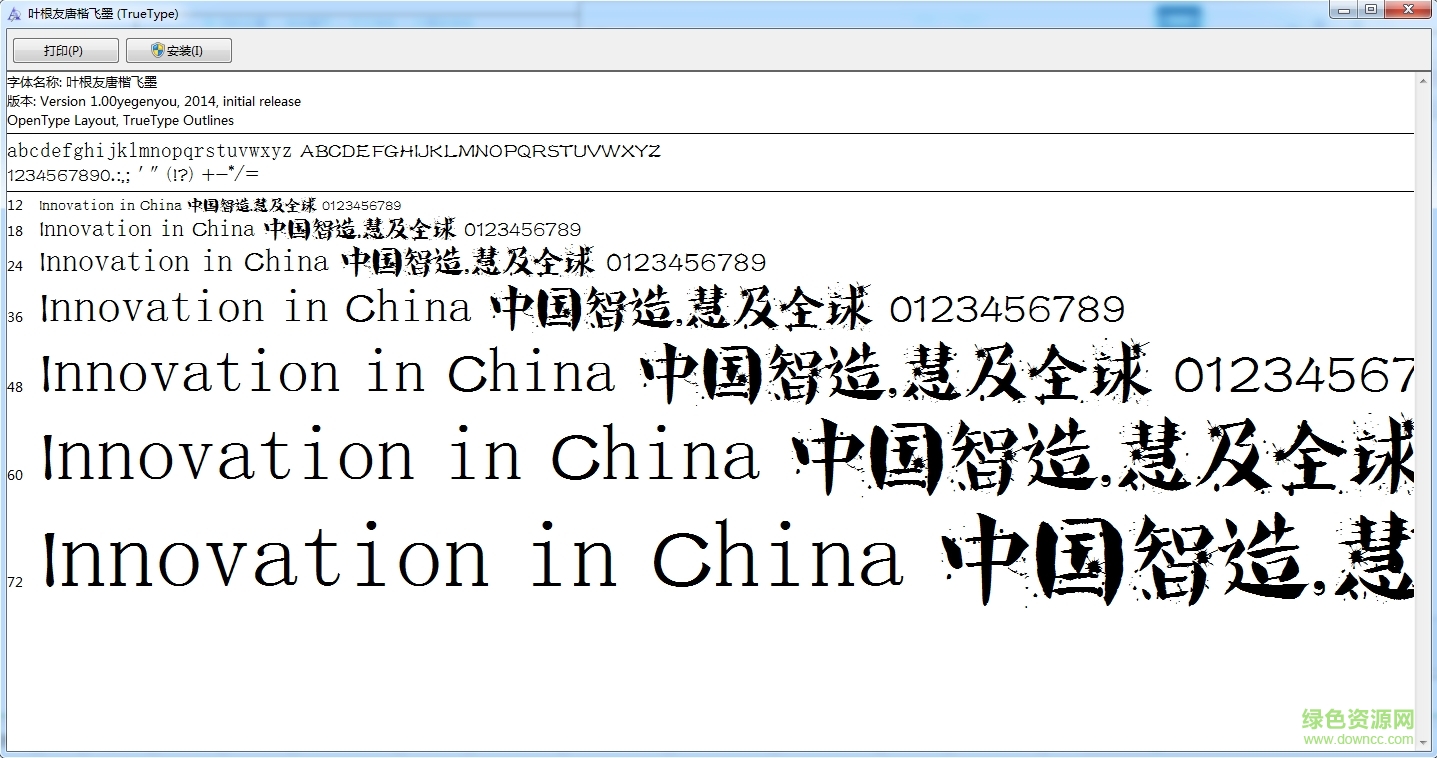
葉根友唐楷飛墨是一款應(yīng)用于設(shè)計(jì)方面的簡(jiǎn)體中文漢字,該字體每一個(gè)字都帶有飛墨痕跡,筆鋒犀利,效果非常出彩,可用于卡通設(shè)計(jì)、廣告設(shè)計(jì)、平面設(shè)計(jì)、印刷包裝、報(bào)紙雜志等行業(yè),喜歡的小伙伴快來綠色資源網(wǎng)下載吧!